En esta ocasión se trata de marcas que vemos comunmente en México y que me he encontrado en Qatar… y claro, no pude reistirme a fotografiar.
¿Qué les parece? Así se ven en Qatar los Starbucks, los Dunkin Donuts, los Baskin-Robbins y los Body Shop.
Interesante es que mantenga el mismo estilo visual aún con otra lengua. ¿Qué opinan?
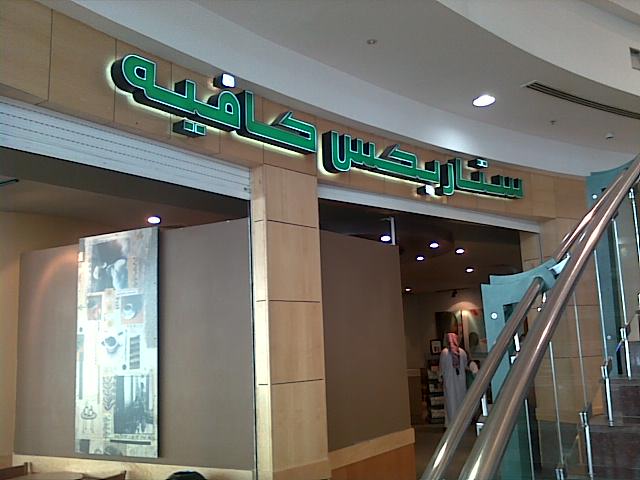
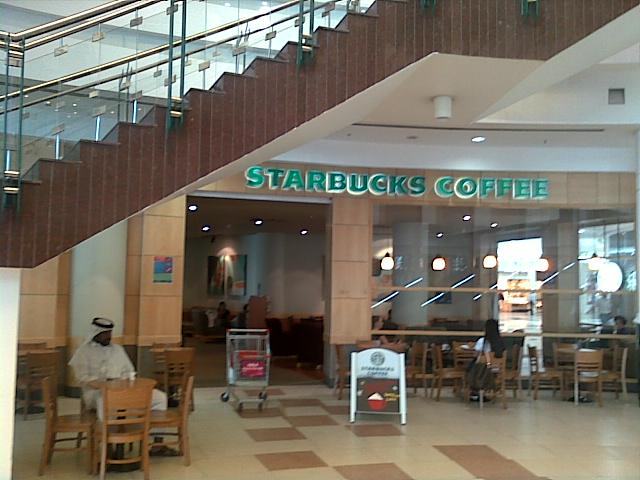
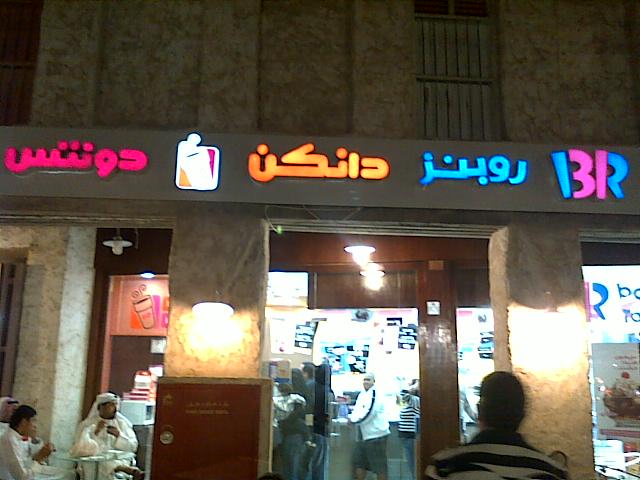
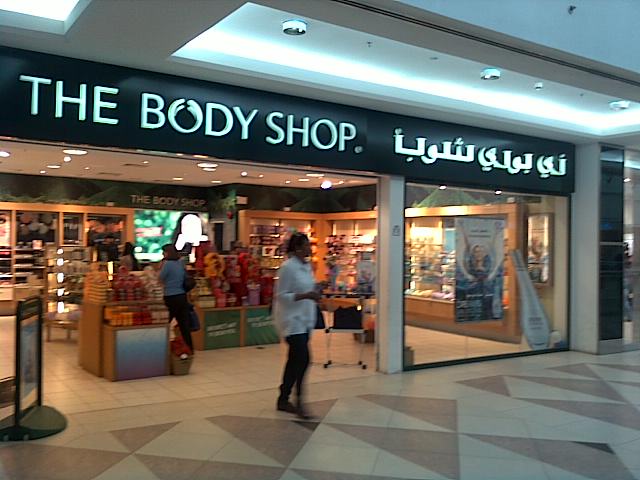
Que padre generar el poder de marca suficiente para lograr esto